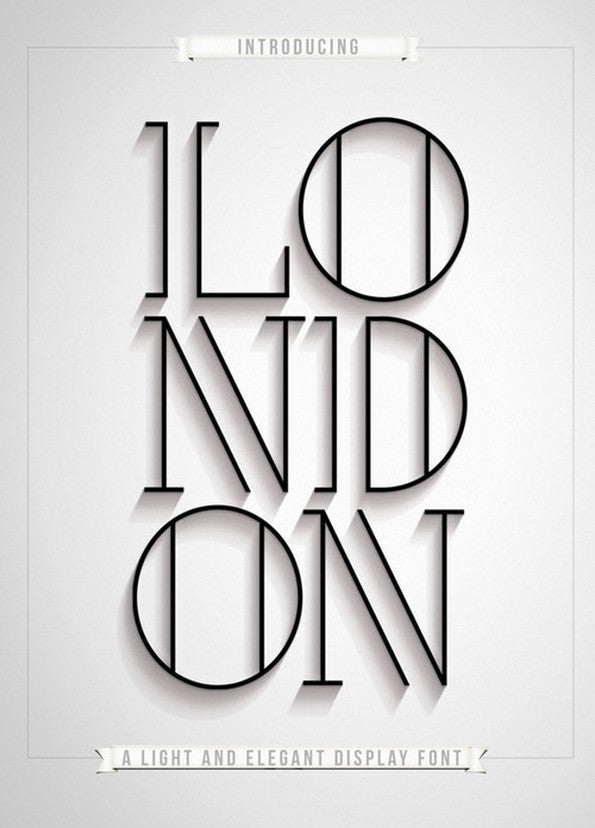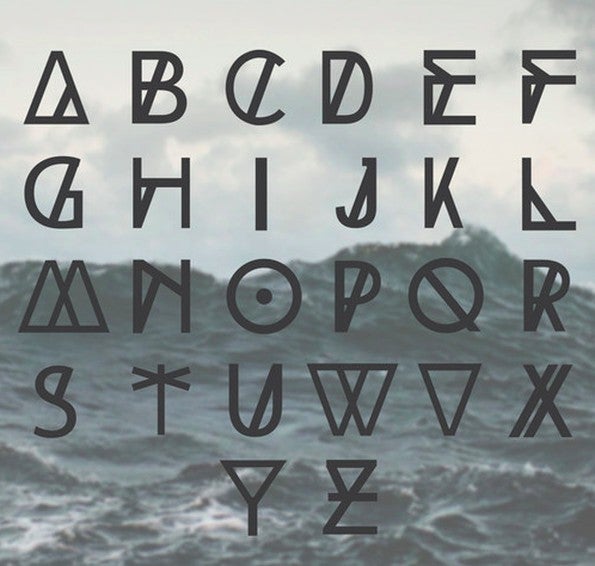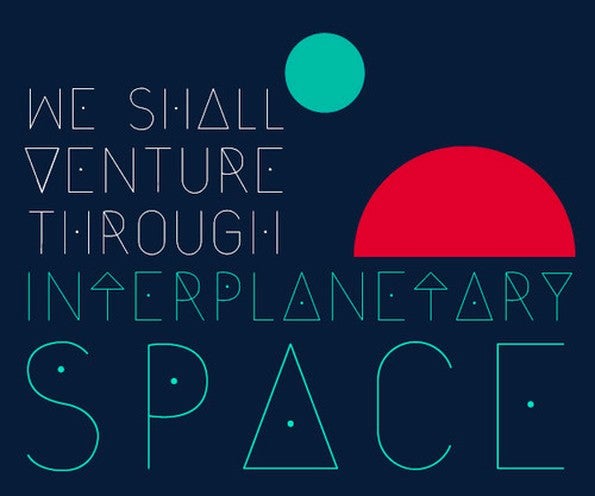
30 kostenlose Fonts für Grafikdesigner
30 kostenlose Fonts: Von Baron bis Facunda
Von den Anfängen der modernen Typografie durch Pioniere wie Nicholas Jenson (1420-1480) bis zum heutigen Tag hat sich viel getan. Von Print bis hin zu verschiedensten Web- und Multimedia-Projekten ist der Bedarf an Fonts höher als je zuvor. Um euch die Suche nach der passenden Schrift für euer nächstes Projekt ein wenig zu vereinfachen, haben wir euch 30 kostenlose Fonts herausgesucht.
Debby
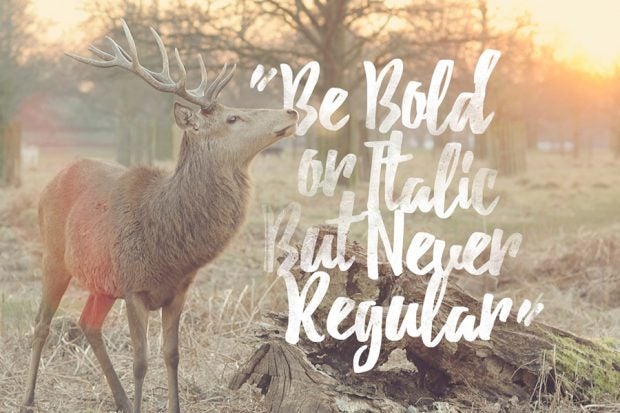
Wer nach einem schicken, handgeschriebenen Font sucht, sollte sich Debby anschauen. (Grafik: Artimasa Studio)
Sk-Modernist
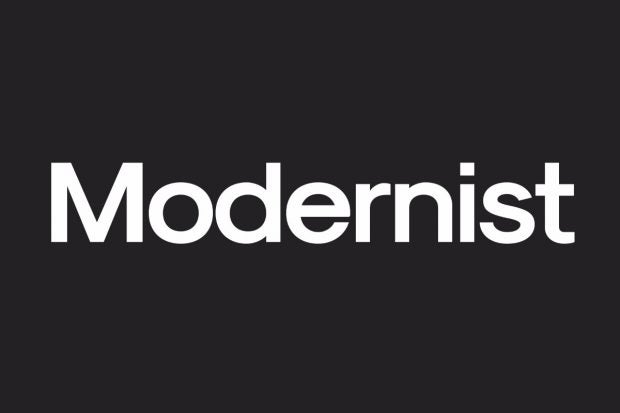
Modernist dürfte all jenen gefallen, die einen minimalistischen Font suchen. Leider ist der Font nur für Printprojekte kostenlos. Für den Einsatz in Web-Projekten wird eine Gebühr fällig. (Grafik: Sean Kane)
Manifesto
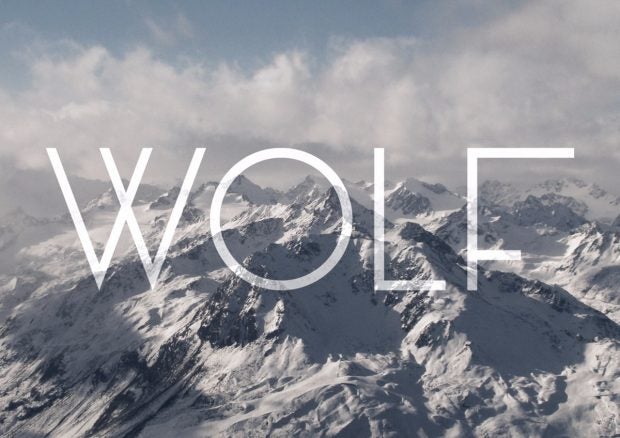
Manifesto soll sich auf den italienischen Rationalismus beziehen. Wir hoffen mal, dass es dabei nicht um die politische Haltung innerhalb der architektonischen Stilbewegung aus den 1920er und 1930er Jahren gehen soll. (Grafik: Tomaz Leskovec)
Manifesto soll sich auf den italienischen Rationalismus beziehen. Wir hoffen mal, dass es dabei aber nicht um die politische Haltung innerhalb der architektonischen Stilbewegung aus den 1920er und 1930er Jahren gehen soll. (Grafik: Tomaz Leskovec)
Suelta
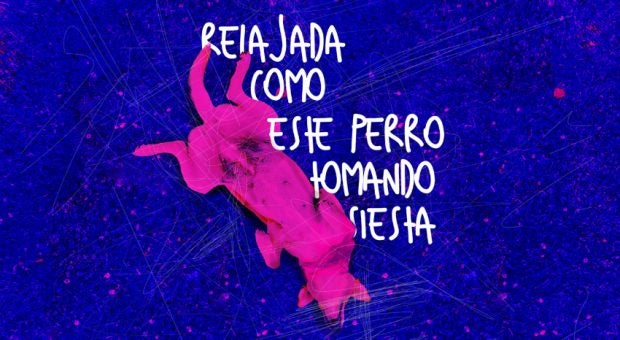
Kostenloser Font: Suelia stammt von den beiden Chilenen Diego Cabrera Ruiz und Rodrigo Alcayaga. (Grafik: Diego Cabrera Ruiz / Rodrigo Alcayaga)
Kostenloser Font: Suelta stammt von den beiden Chilenen Diego Cabrera Ruiz und Rodrigo Alcayaga. (Grafik: Diego Cabrera Ruiz / Rodrigo Alcayaga)
Maquinada
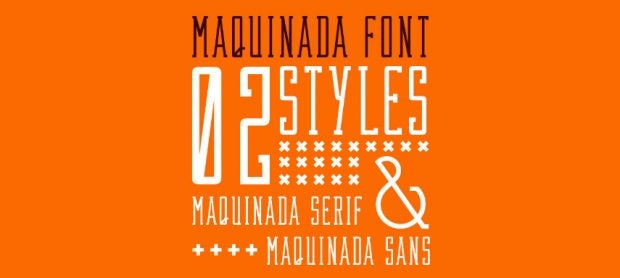
Dieser kostenlose Font wurde von den beiden brasilianischen Designern Henrique Petrus und Gustavo André erstellt. (Grafik: Henrique Petrus / Gustavo André)
Fanwood
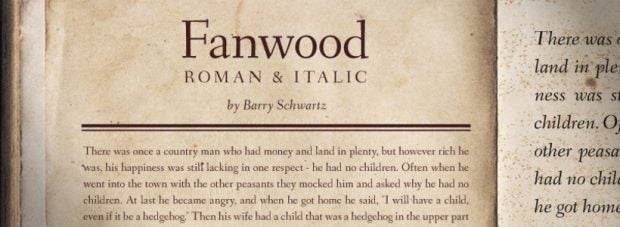
Fanwood orientiert sich an der Arbeit des bekannten Typografen Rudolph Ruzicka. (Grafik: Barry Schwartz)
Soulmarker
Soulmarker ist ein ungewöhnlicher Handschriften-Font. (Grafik: Syed Faraz Ahmad)
Soulmarker ist ein ungewöhnlicher Handschriften-Font aus Indien. (Grafik: Syed Faraz Ahmad)
Cenotaph
Dieser kostenlose Font wurde von dem bekannten Typograf, Grafiker und Bildhauer Eric Gill (1882 bis 1840) inspiriert. (Grafik: Lewis McGuffie)
Maxwell
Maxwell ist eine aus drei Fonts bestehende Font-Family von Ryan Pyae. (Grafik: Ryan Pyae)
Aventura
Kostenlose Fonts: Aventura stammt von dem US-Amerikaner Jimmy Kalman. (Grafik: Jimmy Kalman)
Kust
Kostenlose Fonts: Kust stammt von dem Designer Krišjānis Mežulis. Die einzelnen Buchstaben wurden jedoch von dem Künstler und Modedesigner Ieva Mezule gemalt. (Grafik: Krišjānis Mežulis)
Cavorting
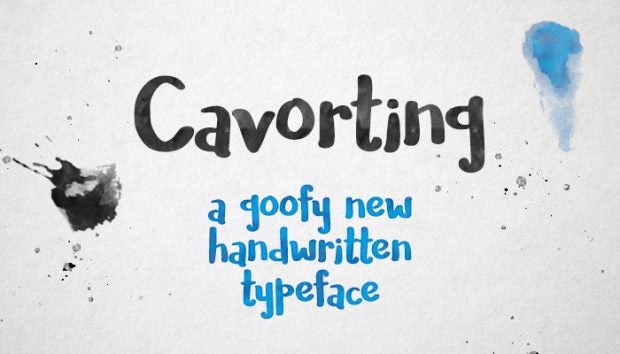
Cavorting: Auch diesen handgeschriebenen Font könnt ihr kostenfrei in kommerziellen Projekten einsetzen. (Grafik: Missy Meyer)
Arca Majora
Der Font stammt von dem Designer Alfredo Marco Pradil aus Dubai. Achtung: Arca Majora bietet ausschließlich Großbuchstaben, aber dafür werden auch Umlaute unterstützt. (Grafik: Behance)